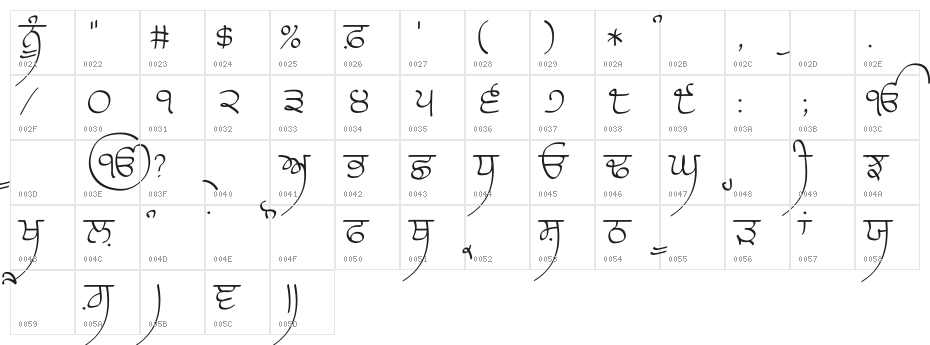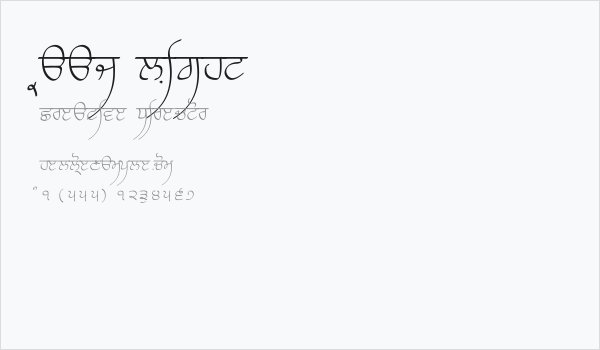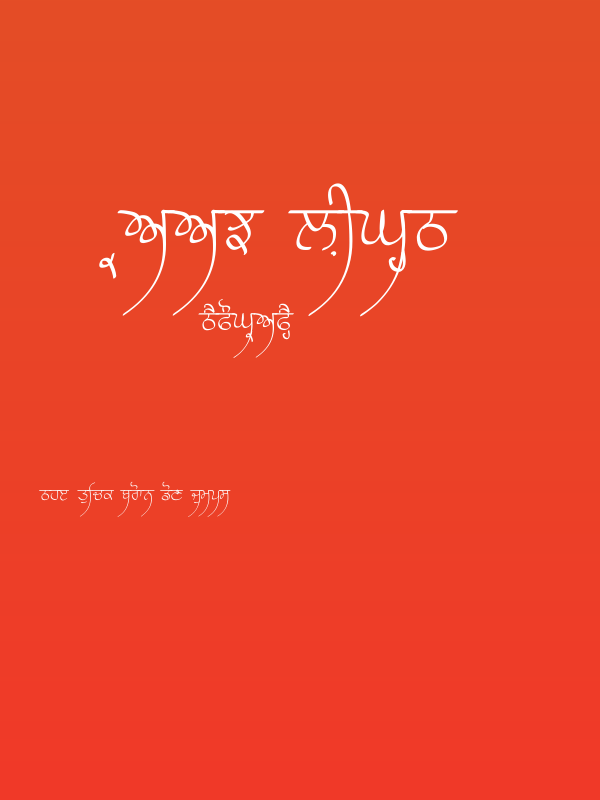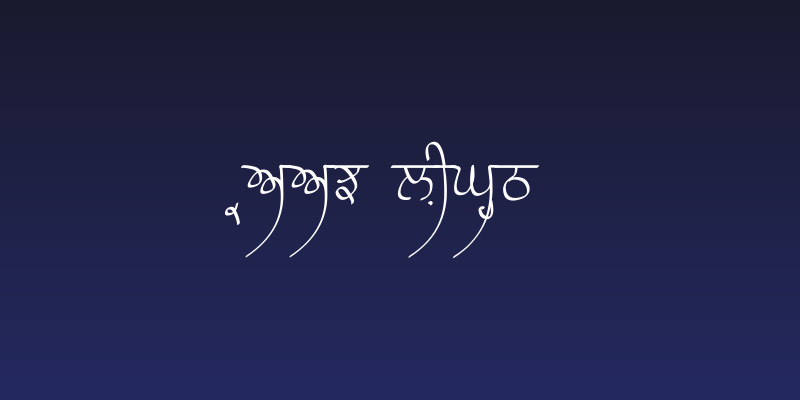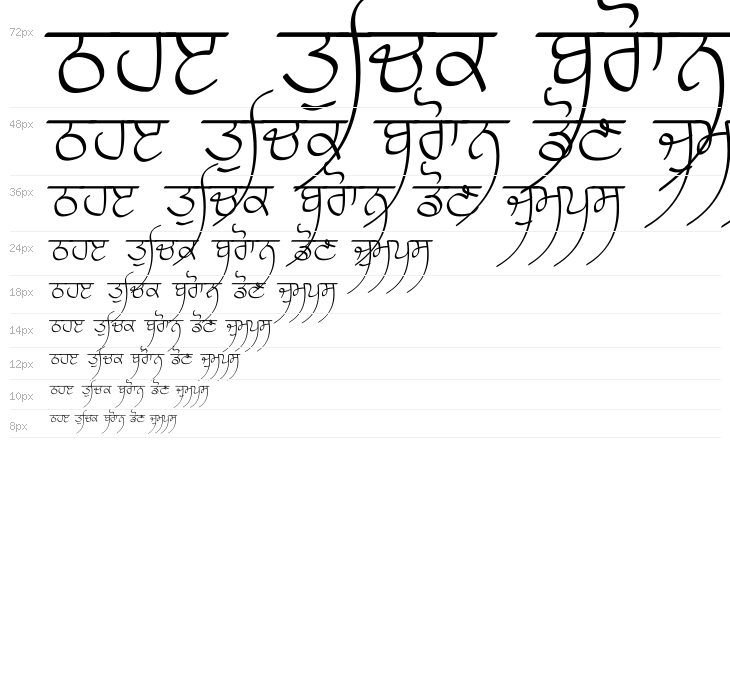
Raaj Light Font
| Nome | Raaj Light |
| Peso | Light |
| Categorie | Asian |
| Stile generale | Traditional |
| Caso d'uso | Headlines, Invitations, Cultural designs |
| Progetti proposti | Ideal for wedding invitations, cultural event posters, elegant branding, and traditional-themed designs. |